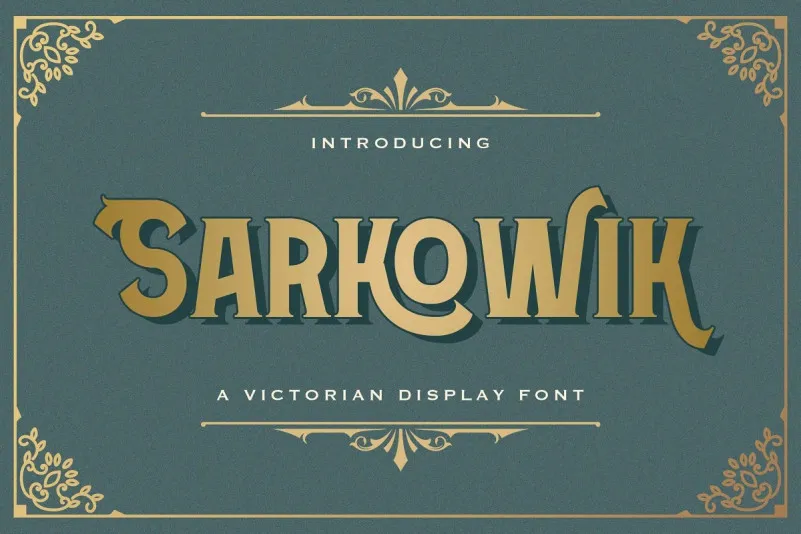
Sarkowik Font – Download Grátis
Esta é uma fonte para displays criada pela StringLabs com serifas anguladas e traços entalhados fortes y destacados. Sarkowik transmite sensação de nostalgia leve, oferecendo um agradável estilo vintage. Inspirado na arte de tatú dos tempos modernos, Sarkowik é uma fonte impecavelmente bela e chamativa. Esta fonte se destaca em uma ampla gama de design tanto moderno quanto clássico, devido à sua forma romântica e ao tom acentuado com detalhes meticulosamente cuidados. Suas proporções dramáticas garantem que Sarkowik seja um elemento visual irresistivelmente atraente para qualquer projeto, seja ele um site de moda vintage ou uma camiseta personalizada com desenhos corporais modernos.